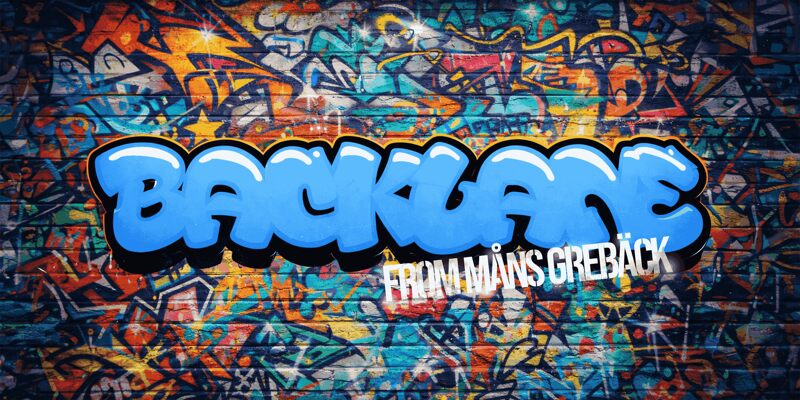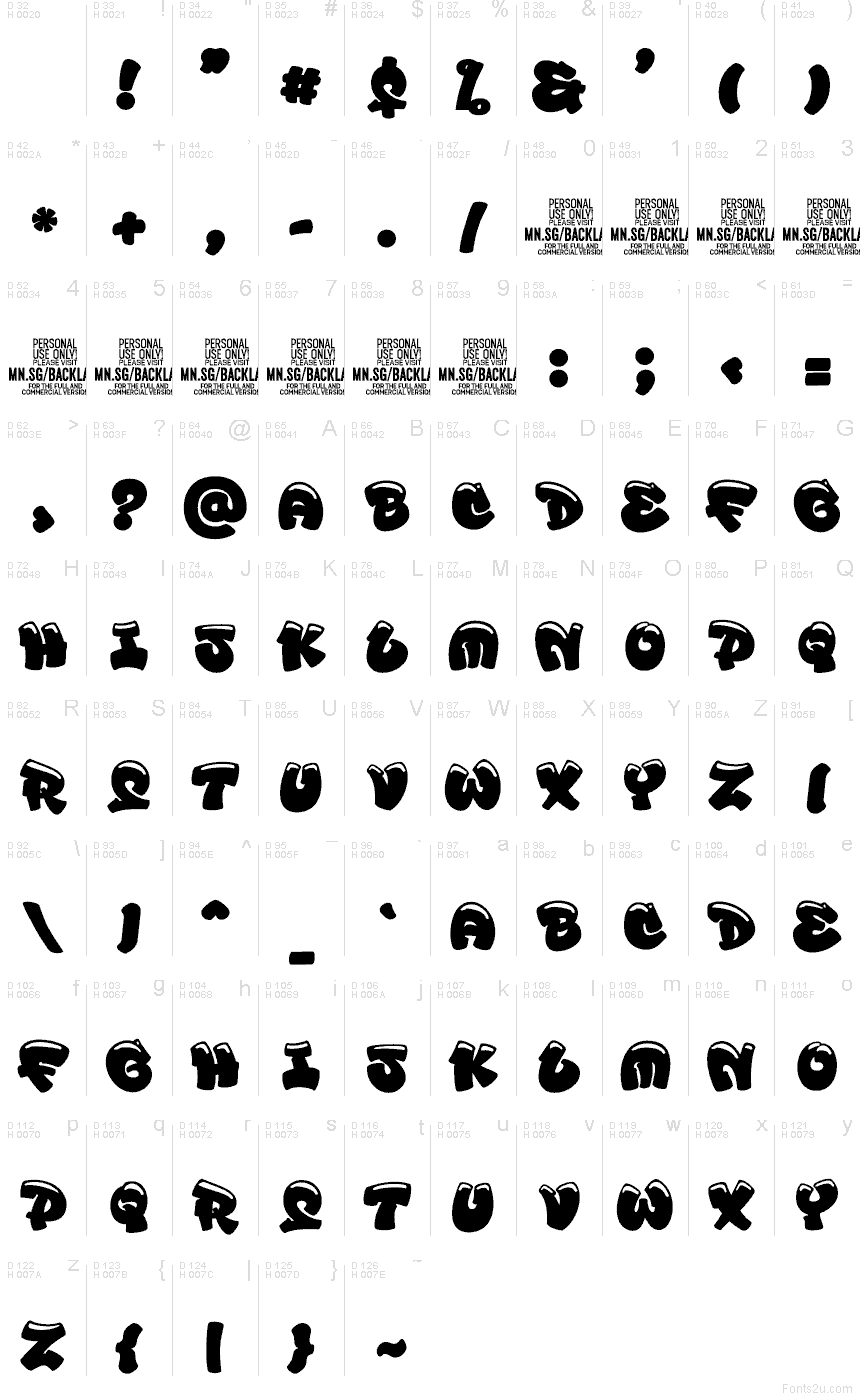
Backlane PERSONAL USE Regular
Backlane von Mans Greback ist eine kostenlose Graffiti-Schrift, die wie pralle Bubble-Lettern geformt ist, mit einer niedrigen, wogenden Skyline und massiven schwarzen Flächen. Die wiederkehrenden weißen Aussparungen an der Oberseite wirken wie feuchte Highlights oder Farbtropfen und verleihen dem gesamten Design einen authentischen Sprühdosen-Look statt eines generischen, abgerundeten Display-Stils.
Diese breite, kompakte Silhouette macht sich hervorragend auf Skate-Postern, Streetwear-Grafiken, Mixtape-Covern, Video-Thumbnails und Sticker-Designs, bei denen die Schrift als einheitliche grafische Geste wirken muss. Kurze Überschriften und Logos profitieren besonders davon, wenn die weichen Kurven und tropfenden Akzente den Vibe von Tags, Throw-ups und bemalten Wänden einfangen sollen.